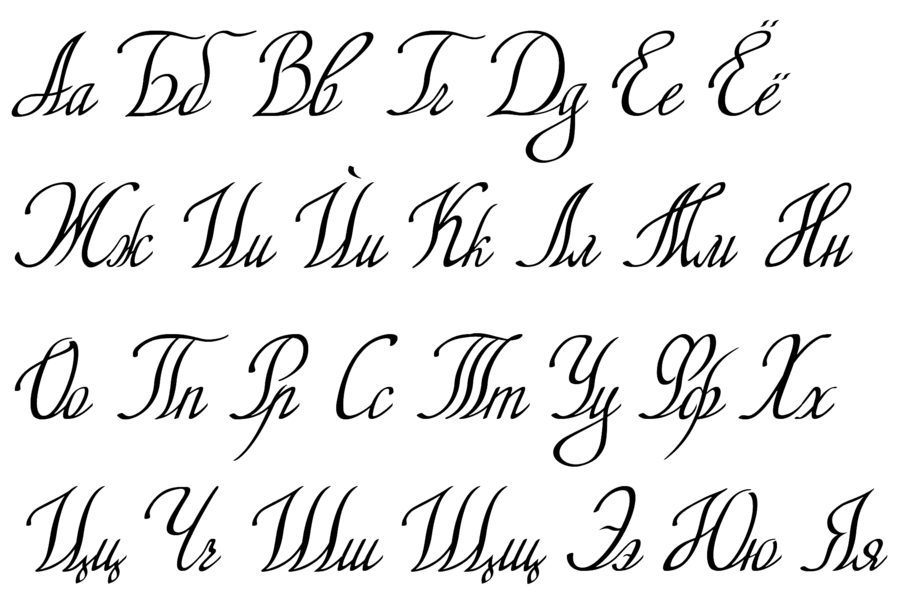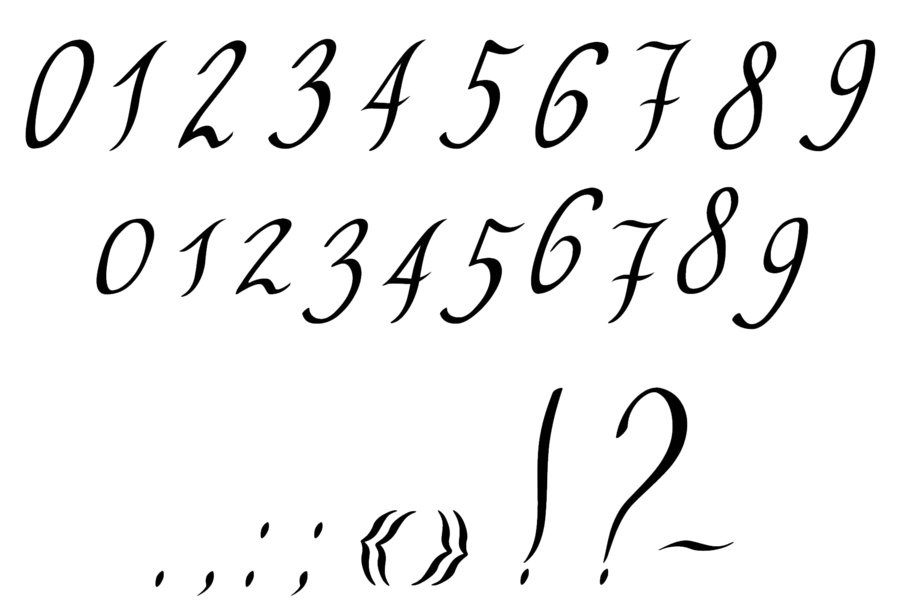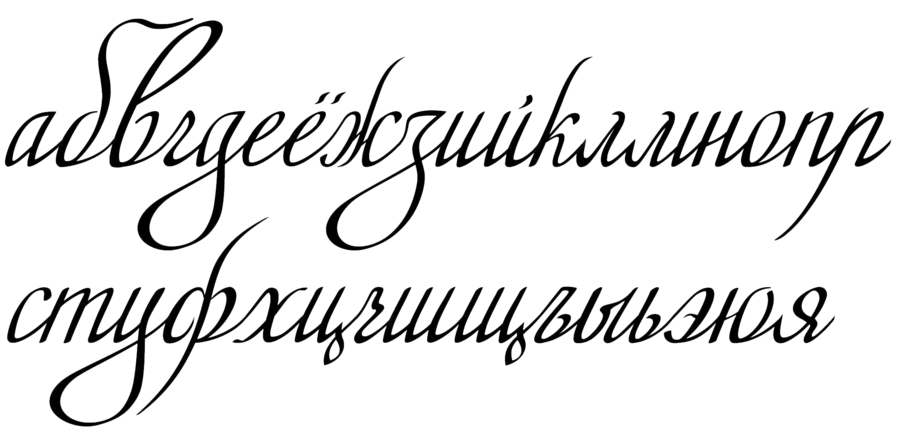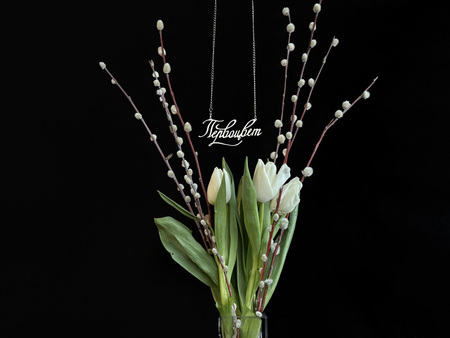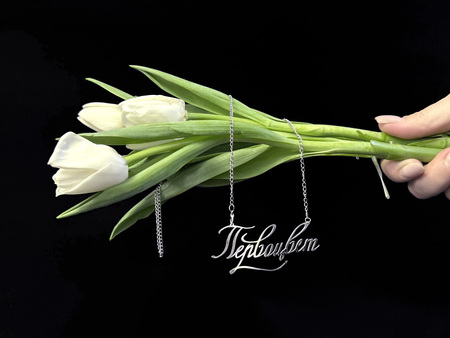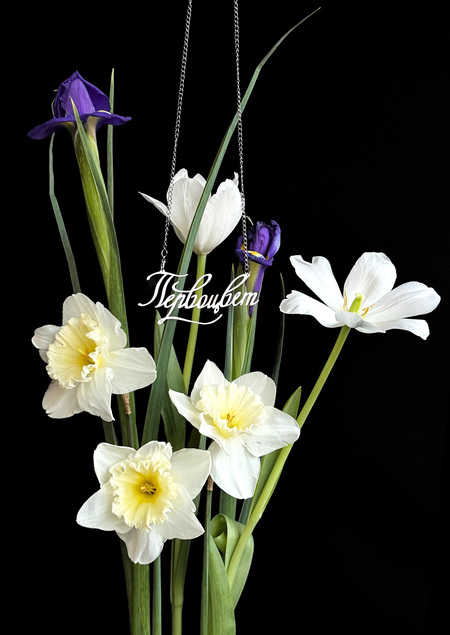
Связный шрифт «Первоцвет» с игривым и лёгким характером, основанный на каллиграфии. Он вдохновлён природными формами и мотивами, которые особенно выразительно проявляются в первых цветочках после холодной зимы.
Алфавит
Цифры и знаки препинания